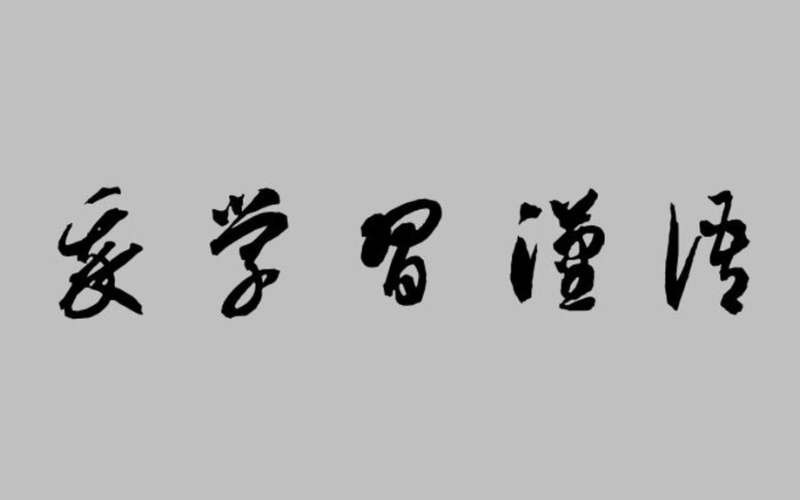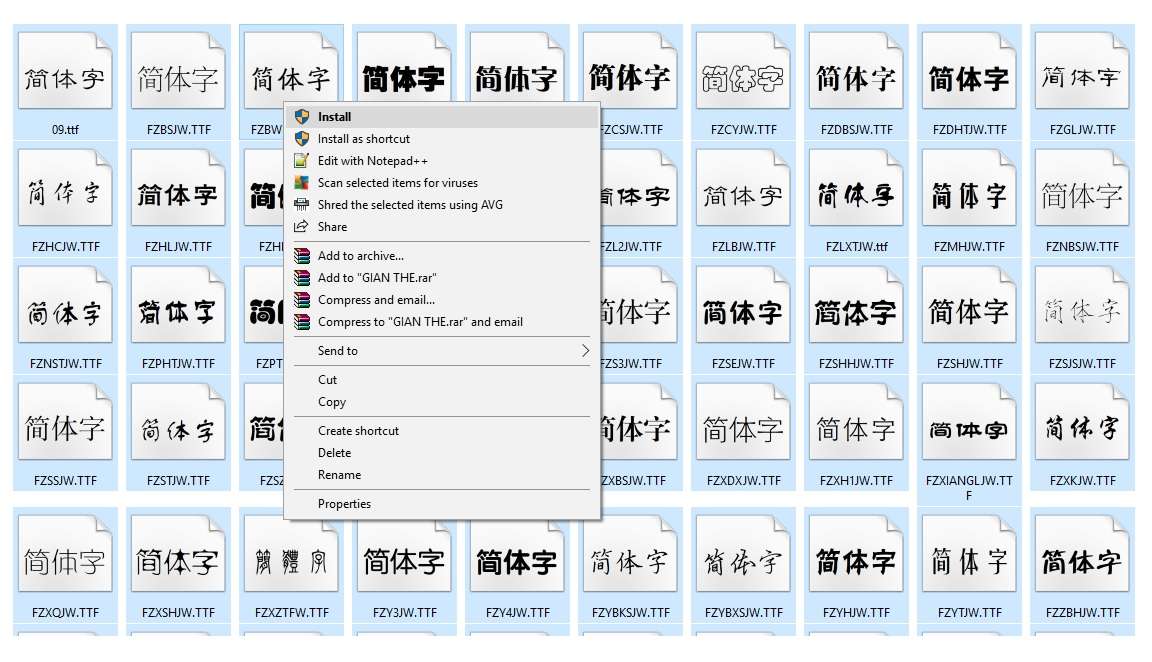
Với những ai đang học tiếng Trung hoặc thường xuyên soạn thảo, phiên dịch, việc lựa chọn font tiếng Trung Quốc đẹp để gõ Hán tự chuẩn là điều vô cùng quan trọng. Sử dụng bộ font phù hợp không chỉ giúp văn bản trở nên rõ ràng, chuyên nghiệp mà còn tạo ấn tượng thẩm mỹ khi trình bày. Bài viết này, Vietkey sẽ giới thiệu những font tiếng Trung phổ biến cùng hướng dẫn cách cài đặt chi tiết, giúp bạn dễ dàng áp dụng ngay trên máy tính và điện thoại.
Font chữ Trung Quốc là gì?
Font chữ tiếng Trung Quốc là các bộ ký tự được thiết kế đặc biệt để hiển thị văn bản tiếng Trung Quốc, bao gồm cả chữ Hán giản thể và chữ Hán phồn thể. Khác với các ngôn ngữ dùng bảng chữ cái, tiếng Trung sở hữu hàng nghìn ký tự riêng lẻ, mỗi ký tự có ý nghĩa và cách đọc riêng. Do đó, font chữ Trung Quốc không chỉ cần đảm bảo hiển thị chính xác các ký tự trên mọi thiết bị và ứng dụng mà còn phải mang tính thẩm mỹ, giúp văn bản trở nên chuyên nghiệp và dễ tiếp nhận.
Ngoài chức năng cơ bản, các font tiếng Trung Quốc đẹp còn ảnh hưởng đến phong cách trình bày của tài liệu, trang web, áp phích hay các sản phẩm quảng cáo. Mỗi font có đặc trưng riêng, từ kiểu đơn giản, dễ đọc đến kiểu nghệ thuật, tinh tế, phù hợp với từng mục đích sử dụng cụ thể.
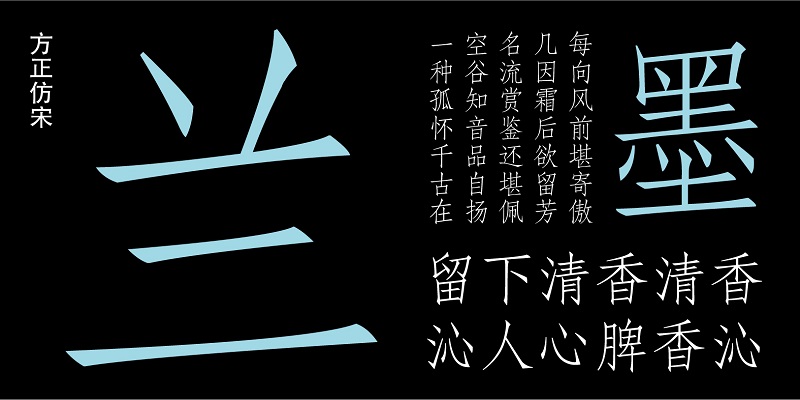
Tại sao font tiếng Trung được sử dụng rộng rãi?
Font tiếng Trung không chỉ phổ biến tại Trung Quốc mà còn được sử dụng rộng rãi ở nhiều quốc gia, đặc biệt trong các cộng đồng người Hoa trên thế giới. Sở dĩ các font tiếng Trung Quốc đẹp trở nên thông dụng là nhờ những lý do sau:
- Sự phát triển của tiếng Trung trên toàn cầu: Với tầm ảnh hưởng ngày càng lớn của Trung Quốc về kinh tế và văn hóa, nhu cầu sử dụng tiếng Trung trong kinh doanh, giáo dục và truyền thông ngày càng tăng.
- Phong cách thiết kế độc đáo: Các font chữ Trung Quốc mang nét nghệ thuật riêng, giúp các nhà thiết kế tạo điểm nhấn cho áp phích, logo, bìa sách hay các sản phẩm sáng tạo khác.
- Đa dạng kiểu chữ: Font tiếng Trung có nhiều phong cách, từ đơn giản, dễ đọc đến tinh tế, phức tạp, đáp ứng nhu cầu từ văn bản học thuật đến tác phẩm nghệ thuật.
- Hỗ trợ kỹ thuật: Các tiêu chuẩn mã hóa như Unicode giúp font tiếng Trung hiển thị chính xác trên nhiều thiết bị và hệ thống, tạo thuận lợi cho người dùng.
- Yếu tố văn hóa: Font chữ là một phần quan trọng của di sản văn hóa và nghệ thuật Trung Hoa, không chỉ là công cụ hiển thị văn bản mà còn mang giá trị thẩm mỹ.
- Cạnh tranh thị trường: Sự phát triển của nhiều font chất lượng cao, kèm giá cả hợp lý, khiến việc sử dụng font tiếng Trung ngày càng phổ biến hơn.
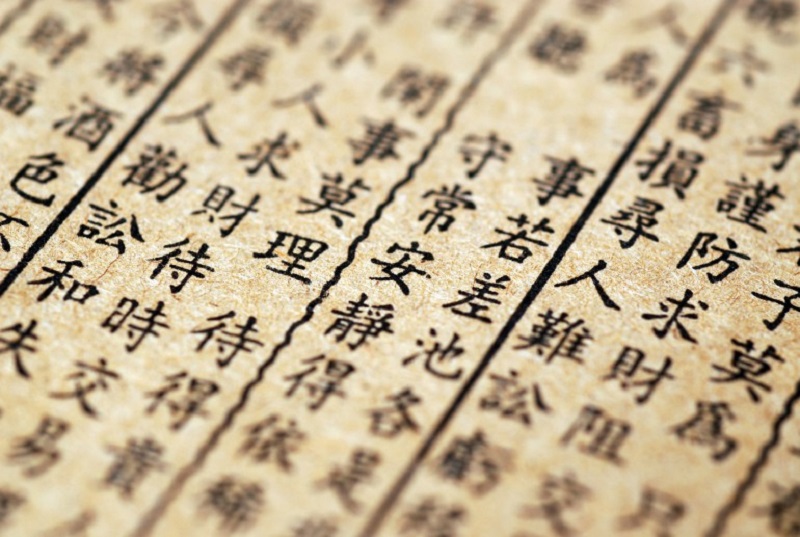
Tổng hợp các font tiếng Trung Quốc đẹp và thông dụng
Việc lựa chọn font chữ Trung Quốc đẹp và phù hợp sẽ giúp văn bản trở nên rõ ràng, dễ đọc và ấn tượng hơn. Dưới đây là những bộ font tiếng Trung Quốc phổ biến, được ưa chuộng trong học tập, thiết kế và soạn thảo, giúp bạn dễ dàng áp dụng cho nhiều mục đích khác nhau:
Font chữ Simsun
Font Simsun là một trong những font tiếng Trung Quốc đẹp giản thể được sử dụng rộng rãi, thường được tích hợp sẵn trên các hệ điều hành như Windows và macOS. Với thiết kế đơn giản, các nét chữ rõ ràng và ngay ngắn, Simsun rất dễ đọc, phù hợp cho tài liệu, bài viết hay nội dung kỹ thuật số, mang đến sự chuyên nghiệp và tiện lợi cho người dùng.
Font chữ DFKAI-SB
DFKAI-SB là font tiếng Trung Quốc đẹp phồn thể, mang phong cách truyền thống với những nét thanh mảnh, thanh thoát. Font này thường được sử dụng trong các tác phẩm nghệ thuật hoặc tài liệu yêu cầu tính thẩm mỹ cao, đồng thời vẫn đảm bảo rõ ràng và dễ đọc cho các ứng dụng hiện đại.
Font chữ Chang Cheng giản thể
Font Chang Cheng giản thể là một trong những font tiếng Trung Quốc đẹp với thiết kế hiện đại và mang tính biểu tượng. Các nét chữ thẳng, chắc chắn giúp văn bản dễ đọc và tạo cảm giác chuyên nghiệp, rất phù hợp cho thuyết trình, poster hay các ấn phẩm truyền thông.
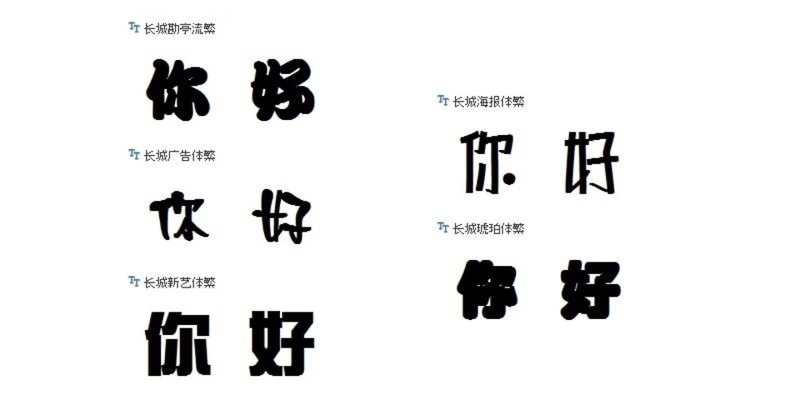
Font chữ KaiTi
KaiTi là một font phồn thể mang phong cách thư pháp Trung Quốc truyền thống, với các nét chữ mềm mại và tinh tế. Font này thường được sử dụng trong các bài thơ, câu đối hay tài liệu văn hóa, mang đậm giá trị nghệ thuật và nét hoài cổ, thích hợp cho những sản phẩm cần vẻ đẹp cổ điển và trang nhã.
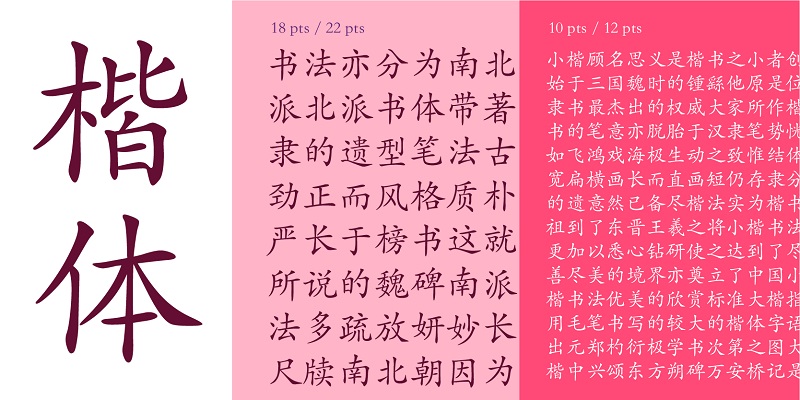
Font chữ Lệ
Font Lệ, hay còn gọi là Lishu, là một kiểu chữ cổ điển của Trung Quốc, kết hợp hài hòa giữa các nét thẳng và cong. Với tính nghệ thuật cao, font này thường được sử dụng trong thư pháp và các thiết kế mang phong cách trang trọng, mang đến vẻ đẹp truyền thống và thanh lịch cho văn bản.
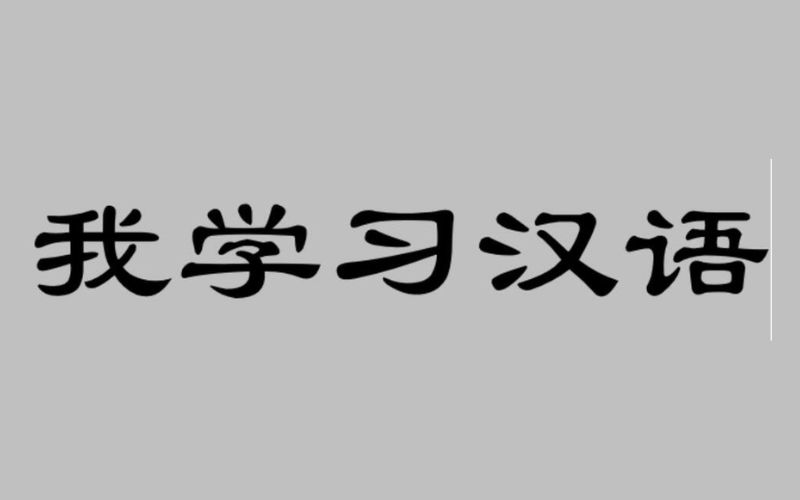
Font chữ Hành
Font Hành, hay Xing Shu, là một trong các font tiếng Trung Quốc đẹp mang phong cách thư pháp bán chính thức, kết hợp sự mềm mại của chữ Thảo với độ rõ ràng của chữ Chính. Font này thường xuất hiện trong văn học cổ điển và các tác phẩm thư pháp nghệ thuật, mang đến sự uyển chuyển nhưng vẫn dễ đọc cho văn bản.
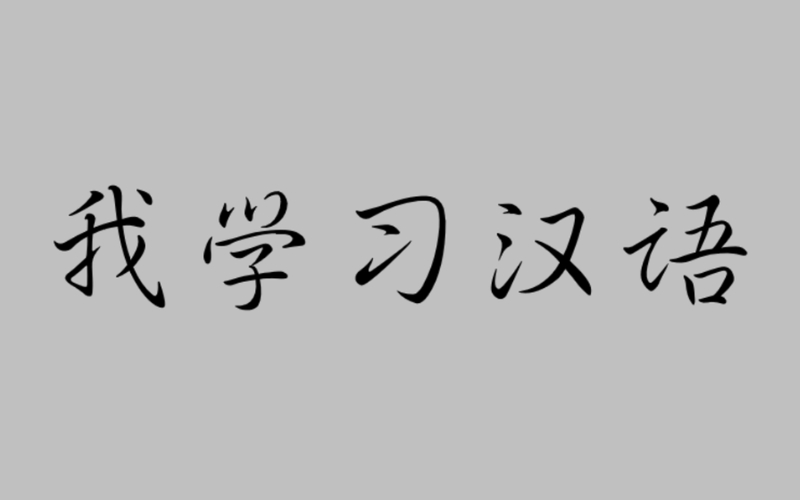
Như vậy, các font tiếng Trung Quốc đẹp không chỉ giúp văn bản trở nên rõ ràng, dễ đọc mà còn góp phần thể hiện nét văn hóa và thẩm mỹ đặc trưng của Trung Hoa. Tùy theo nhu cầu học tập, thiết kế hay trình bày, bạn có thể lựa chọn font phù hợp để tạo ấn tượng chuyên nghiệp và tinh tế. Hy vọng qua bài viết này, bạn đã tìm được những bộ font ưng ý và biết cách cài đặt dễ dàng trên thiết bị của mình.